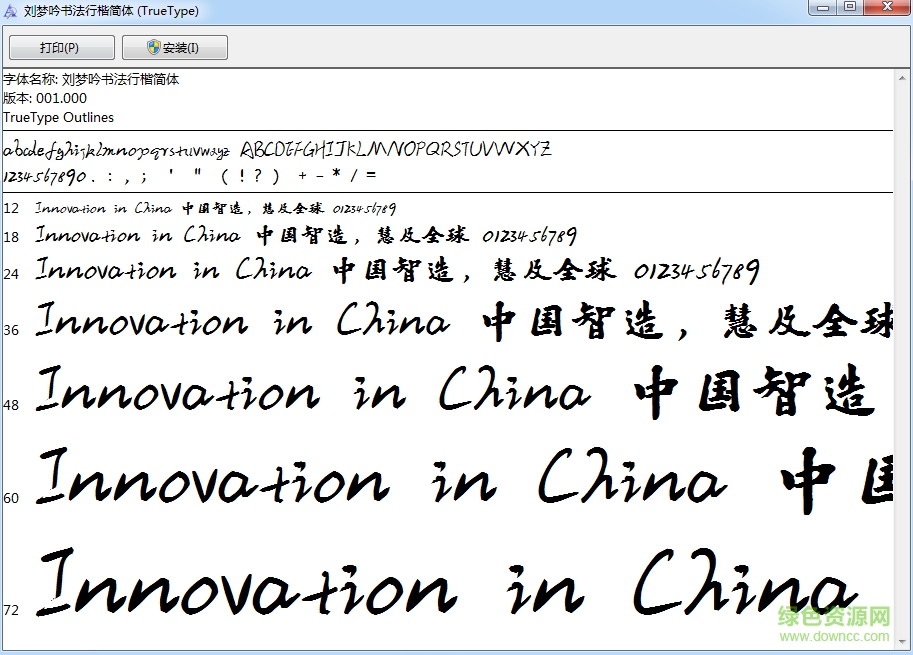
劉夢(mèng)吟書法行楷繁體字體是一款非常引人注目的書法字體,筆畫舒緩自如,疏密得當(dāng),線條變化適度,結(jié)構(gòu)分布合理,美觀又實(shí)用,需要的朋友快來綠色資源網(wǎng)下載收藏吧!
【行書字體】
行書是楷書的快寫,相傳始于漢未,它不及楷書的工整,也沒有草書的 草案.行書中帶有楷書或接近于楷書的叫做"行楷",帶有草書或接近于草書的叫 "行草".